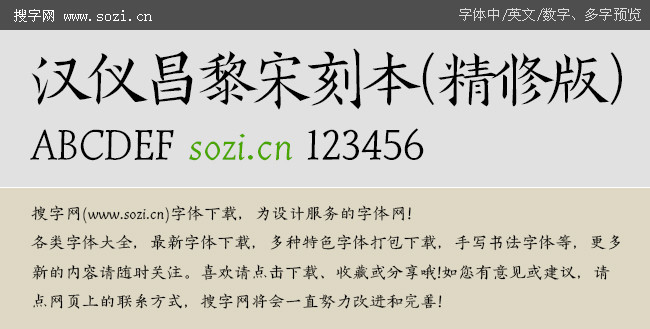
漢儀昌黎宋刻本(精修版)
搜字網(wǎng)給大家提供一款漢儀昌黎宋刻本(精修版)中文字體下載,漢儀昌黎宋刻本(原版)字體優(yōu)美清新,線條流暢,樸素?zé)o華,飽含古時(shí)之風(fēng)韻,能帶給人們一種懷舊感覺(jué),適合應(yīng)用于書(shū)籍設(shè)計(jì)、平面海報(bào)設(shè)計(jì)、傳統(tǒng)包裝設(shè)計(jì)等應(yīng)用。(本字體為個(gè)人非商用版,如需要商用請(qǐng)聯(lián)系漢儀公司購(gòu)買(mǎi)版權(quán))